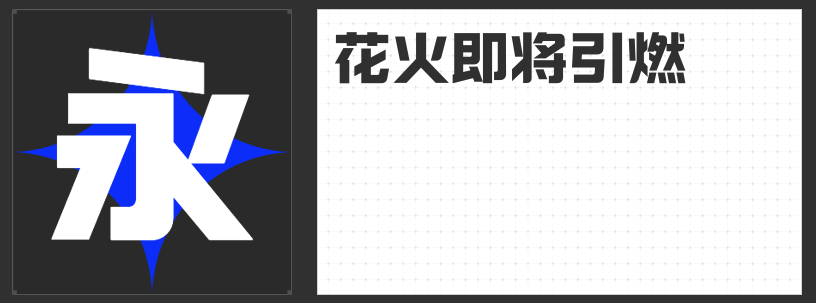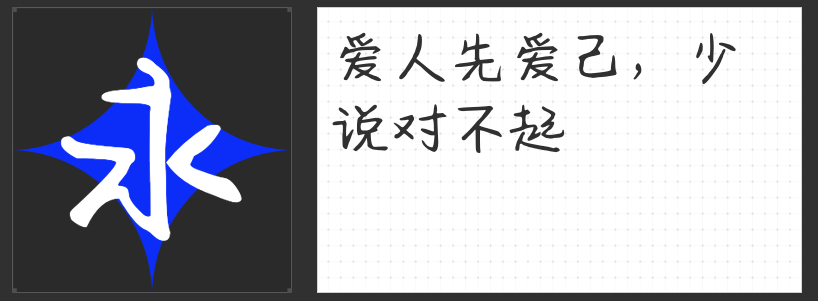
四款创意字库字体:解锁设计新维度的视觉密码
在设计的广阔天地中,字体是传递信息与情感的隐形桥梁。一款恰到好处的字体,能瞬间提升作品的格调与感染力。今天,为大家推荐四款各具特色的创意字库字体,为设计注入独特魅力。
这款字体以无衬线装饰的极简风格,展现出笔划的粗壮有力。撇捺等笔画摒弃尖锐,横直均匀分布,视觉上突出醒目。它仿佛一位坚定的守护者,在标题、导语、标志等设计中,以其强烈的存在感迅速抓住受众目光,传递出果敢、坚毅的气质,为作品奠定坚实有力的基调。
字形结构端正,笔画清晰流畅,整体风格清秀别致。它如同青春时期的一抹亮色,灵动而不失优雅。无论是短视频中快速切换的画面,还是海报上精心布局的文字,它都能完美适配,以简洁大方的姿态承载信息,在不经意间触动人心,展现出青春的活力与美好。
圆润饱满的字形是这款字体的最大亮点,自然的弧线与柔和的转角,让每个字都仿佛带着微笑,散发出无尽的亲和力。在儿童相关领域的设计中,它无疑是绝佳选择。书籍设计里,它能营造出温馨的阅读氛围;包装上,它能吸引孩子们的目光;品牌宣传与海报设计中,它以可爱的形象拉近与受众的距离,为设计增添童真趣味。
作为一款随性、放松的手写字体,它以自然、连贯、轻快的书写风格独树一帜。笔画形态、运笔节奏与字形结构中,都融入了随性的手写感,呈现出自然、温和且富有生活气息的特质。在包装、封面设计、海报设计、影视宣传等场景中,它能传递出真挚的情感,让作品更具温度与人文关怀。
这四款创意字库字体,各具特色,为设计师提供了丰富的选择,助力打造出更具个性与魅力的作品。